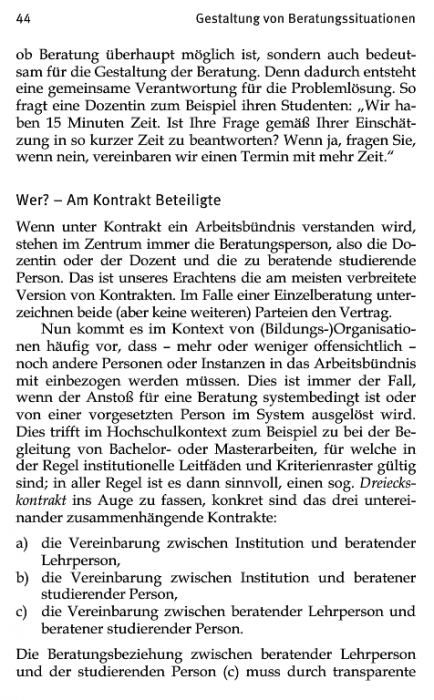
Palatino und Meta? Passt das? Was passt besser?
Mein anderswo schon mal erwähntes Buchprojekt wird jetzt anscheinend in der Kombination Palatino und Meta gesetzt. Ich habe allerdings beim Verlag noch etwas Mitspracherecht, was das Design angeht. Deshalb wollte ich euch mal um Rat fragen.
Unten ein Beispiel einer Seite eines ähnlich gesetzten Buches. Ich finde die Kombination recht unglücklich, kann aber nicht genau sagen warum. Ich glaube ich finde den ganz ähnlichen Grauwert von Überschrift und Fließtext nicht gut. Die Überschrift geht unter, oder? Reicht es, die Überschrift einfach in einem fetteren Schnitt zu setzen? Aber irgendwie stört mich auch Laufweite und Schriftgröße von der Meta in dieser Kombination.
Ich hatte ja gehofft, der Fließtext würde in Minion Pro gesetzt werden, aber auch da bin ich noch nicht davon überzeugt, sie mit der Meta zu kombinieren.
Was meint ihr?
Im Beispiel finde ich folgendes ungünstig:
• Die Größenunterschiede der Kopfzeile und Überschrift zum Lesetext wirken auf mich beide unentschlossen.
• Der Zeilenabstand im Fließtext könnte größer sein
• Womöglich sollte man auch etwas sperren.
Wenn das alles korrigiert ist, müsste man sich nochmal die Schriftwahl ansehen. Unter Umständen lässt sich dann sogar mit der Palatino arbeiten. Ich persönlich würde aber lieber eine frischere und freundlichere Antiqua wählen: Naheliegend wäre die Meta Serif, aber auch die Meret könnte passen … oder eine andere Barock-Antiqua.
Danke für deine Antwort, R::bert. Also liegt es womöglich gar nicht an der Kombination der beiden, dass ich den Anblick nicht besonders attraktiv finde, sondern nur an der Präsentation. Du meinst also, dass Sperrung und Zeilenabstand der Palatino eher an die Meta angeglichen werden sollten?
Ich tue mich mit dem Grauwert von Texten meistens etwas schwer. Es ist wahrscheinlich komplett subjektiv, aber ich finde eine Überschrift sollte immer irgendwie im Kontrast zum Fließtext stehen. So ein komplett blassgrauer Anblick schreckt mich insbesondere bei Sachbüchern stark ab.
Klar, Du kannst die Meta auch über einen fetteren Schriftschnitt absetzen. Das würde ich aber erst dann in Betracht ziehen, wenn man sieht, wie sich die »Skelette« überhaupt miteinander vertragen. Da diese formal jeweils einem anderen Prinzip folgen (Meta eher barock, Palatino humanistisch) ist ein höherer Kontrast (durch Größe und Strichstärke) aber höchstwahrscheinlich zu empfehlen. :-)
Mir scheint die Palatino auf jeden Fall ein wenig zu eng eingestellt zu sein, da wirst Du womöglich auch mal die Blocksatz-Werte (minimale und maximale Buchstaben-Abstände, etc.) angleichen müssen. Und welches Kerning nutzt Du: optisch oder metrisch? Beim »Wenn« steht das W ziemlich alleine da …
Entweder die FF Meta fetter (zb Bold) oder eine andere Textschrift. Aber auch da wird der Kontrast zu gering sein, also Zwischenüberschriften entweder größer oder fetter; dann können sie sogar kleiner sein.
Übrigens passen Minion und Meta gut zueinander. Weil ich diese Kombination lange verwendet hatte, kam es zum Entwurf der MetaSerif. Die ist absichtlich unspektakulär und soll eher wie Times oder Minion als unauffällige und sparsame Textschrift dienen.
Vielen Dank für eure Tipps. Ich werde mich voraussichtlich nächste Woche mit der Redakteurin über diese Themen unterhalten, um so indirekt mit der Setzerin einzelne Designaspekte abzusprechen. Der Verlag ist da sehr nett und wünscht, dass Autoren am Ende auch mit Layout etc. zufrieden sind.
Die Kombination Minion und Meta Bold würde mir sehr gut gefallen, aber so wie im Beispiel oben waren die letzten Bücher eher in Palatino gesetzt. Ich habe in gewisser Weise das Glück, dass mein Band der erste in einer Reihe sein wird. Wir können also das Schriftbild festlegen. ;-)